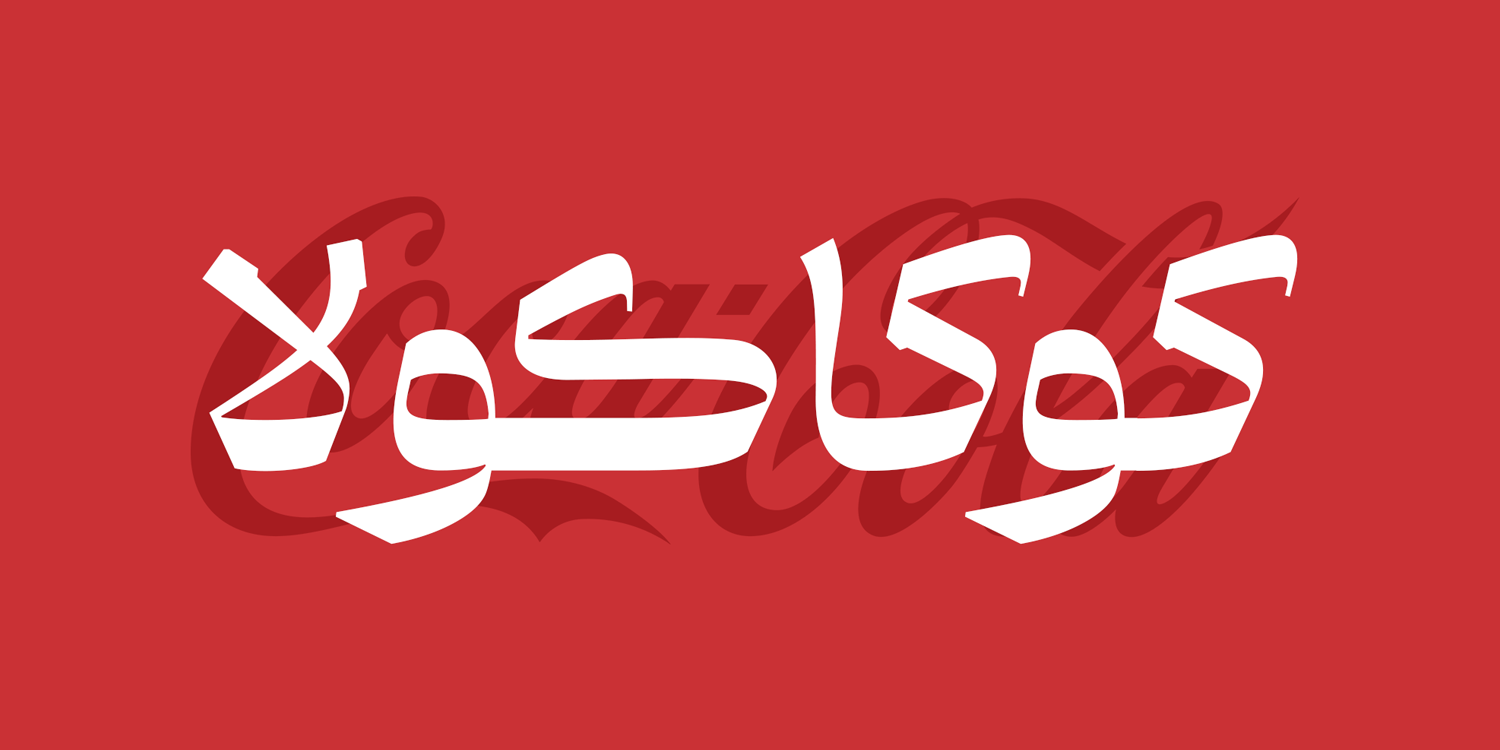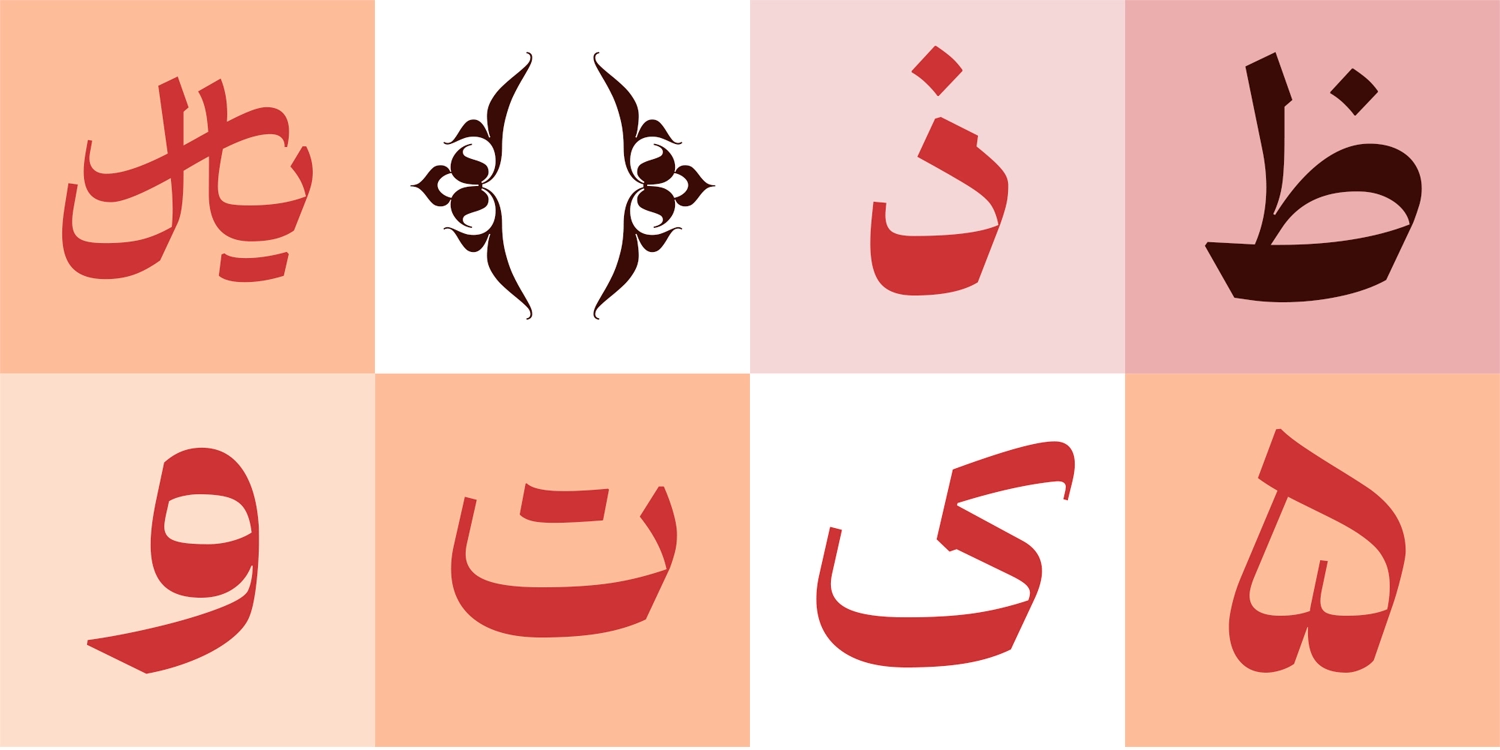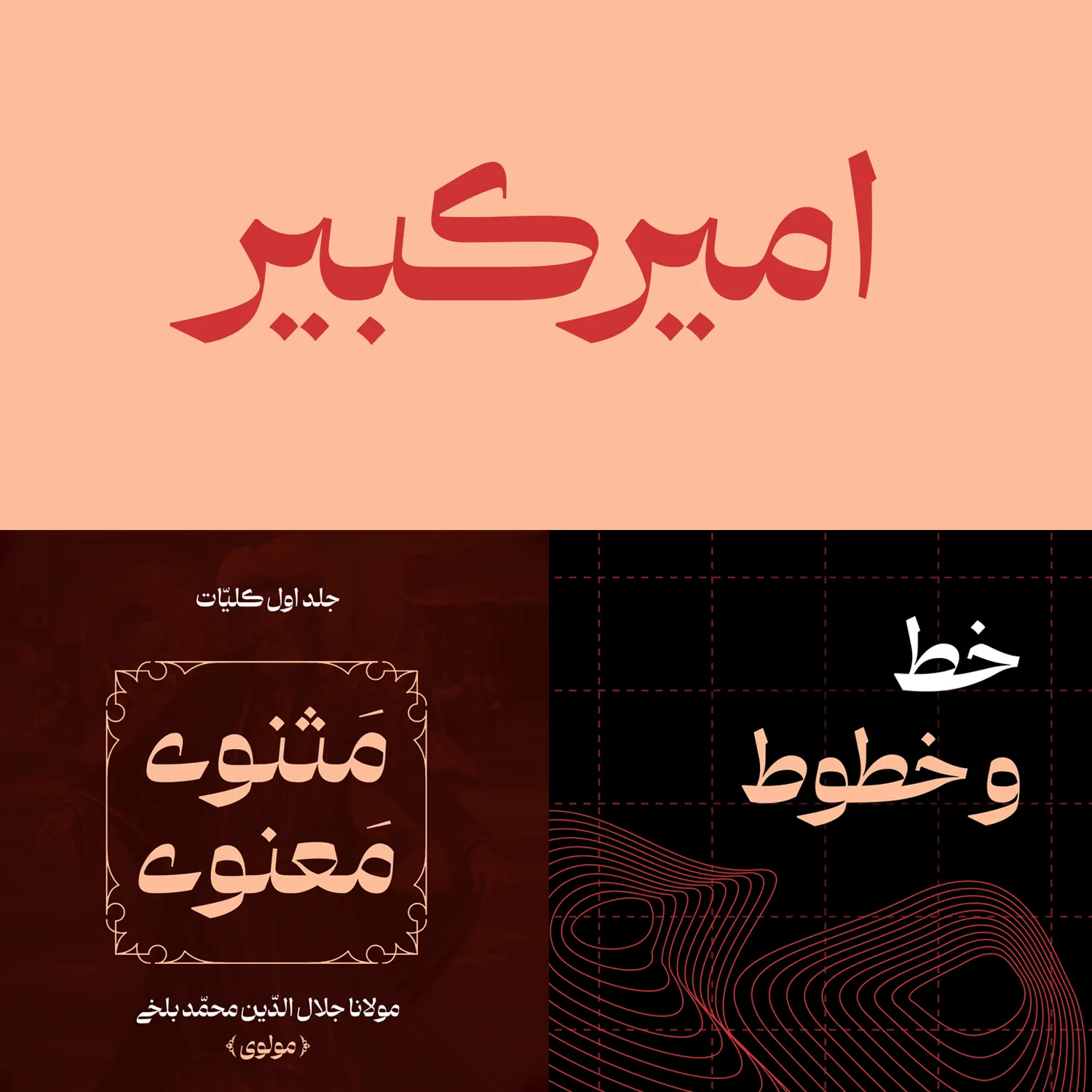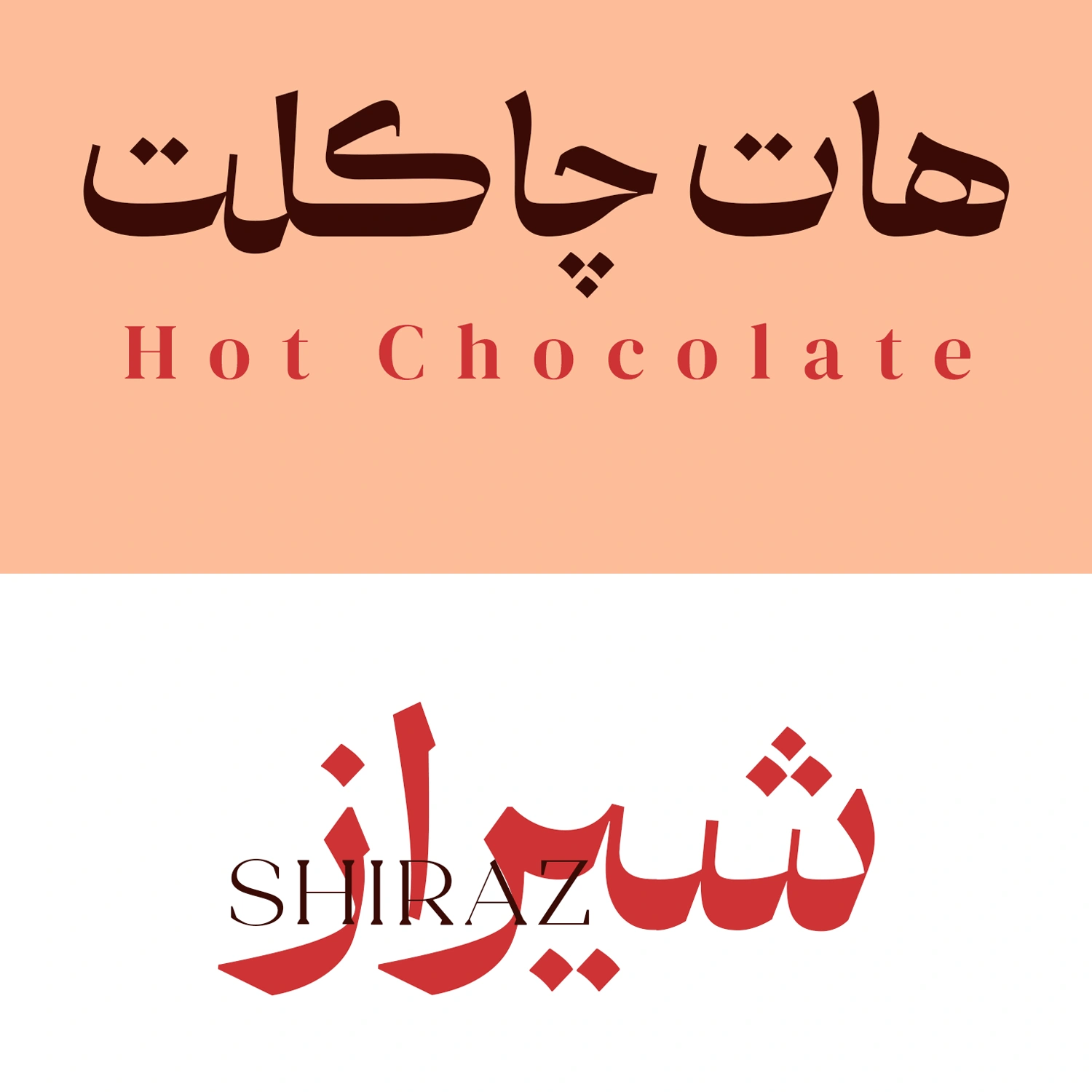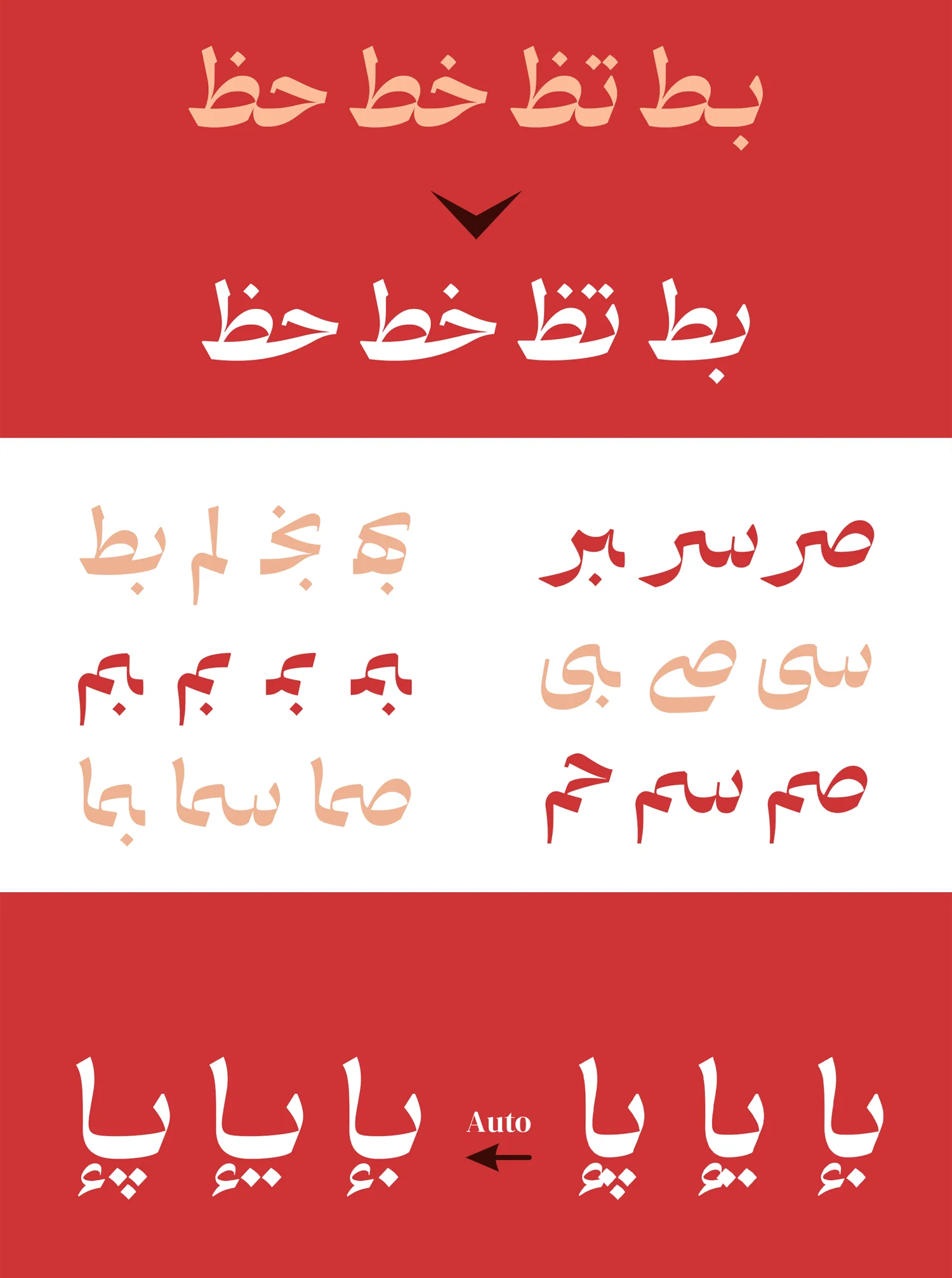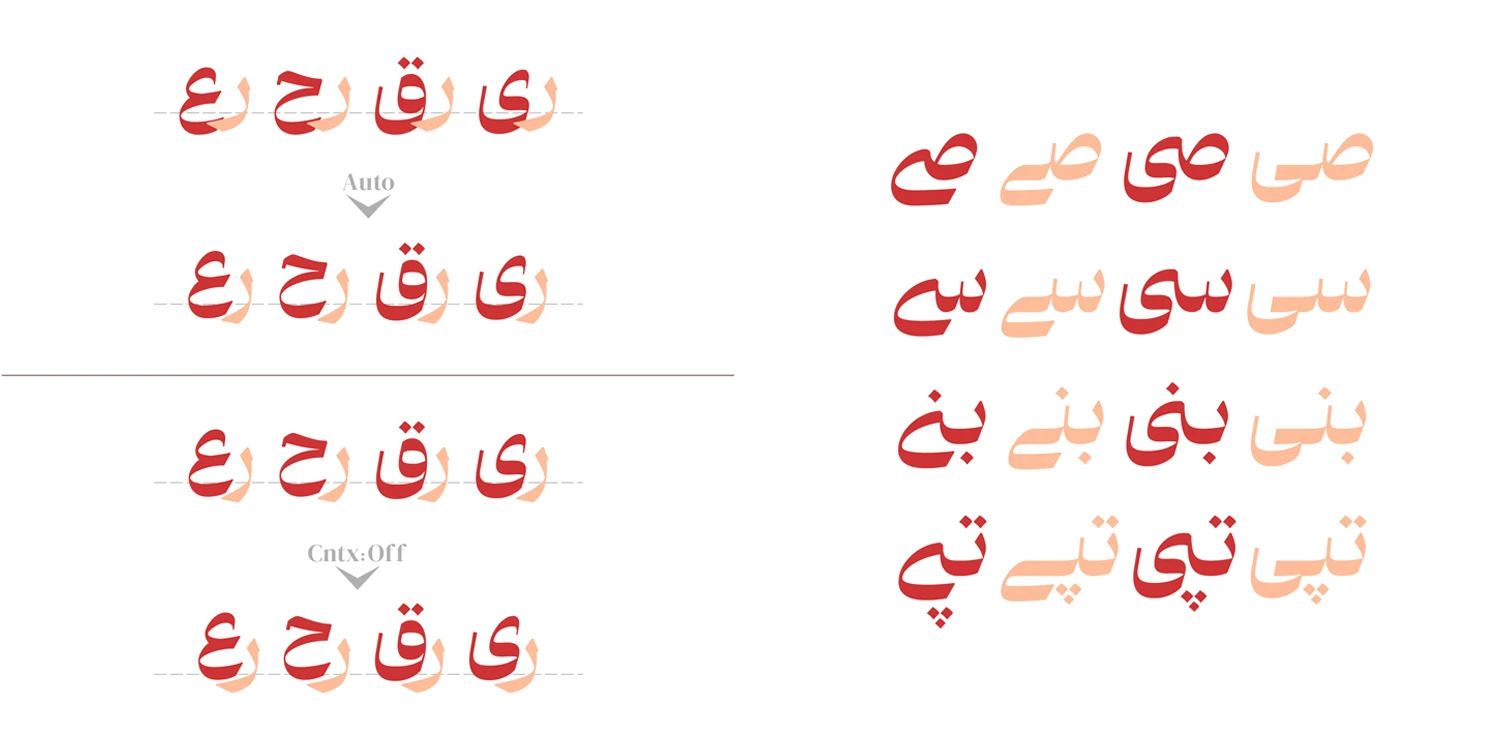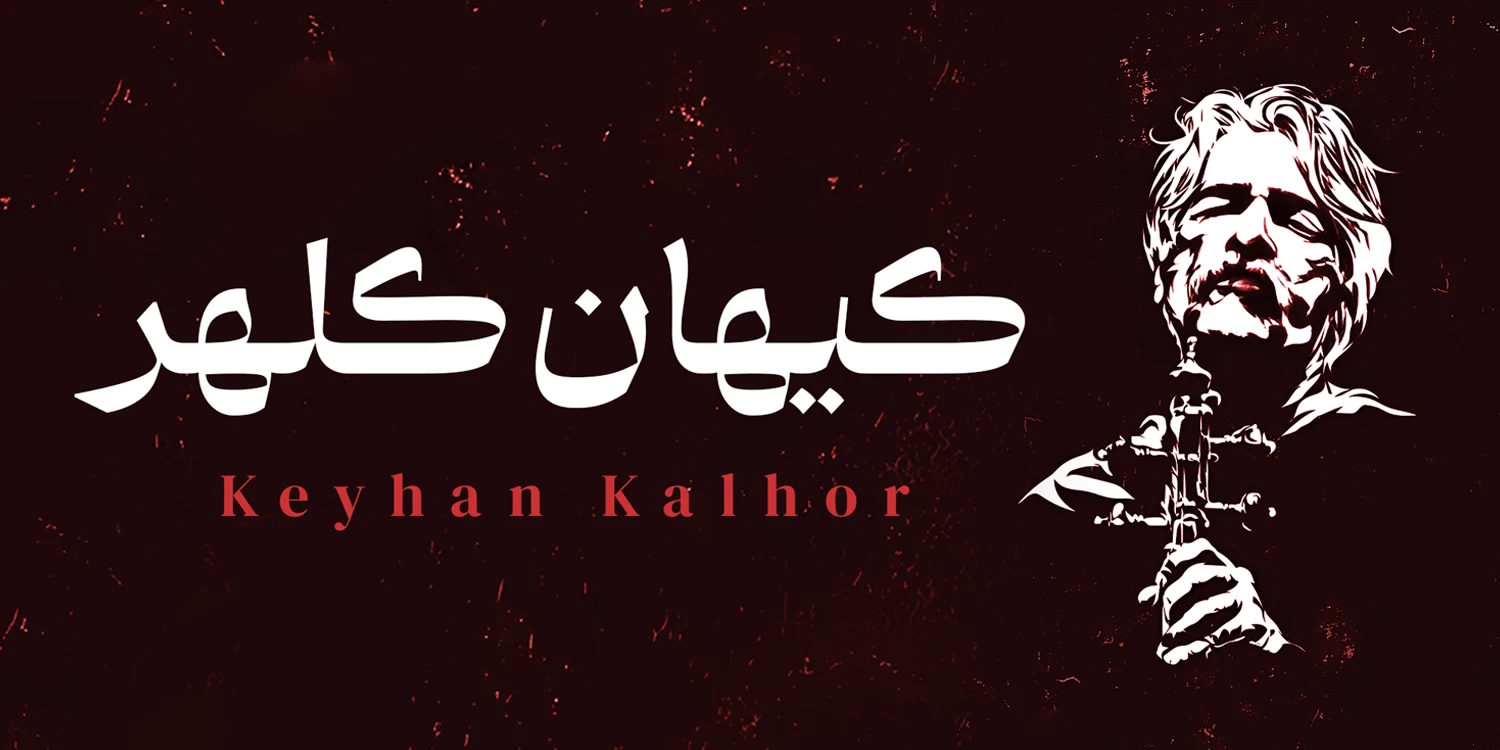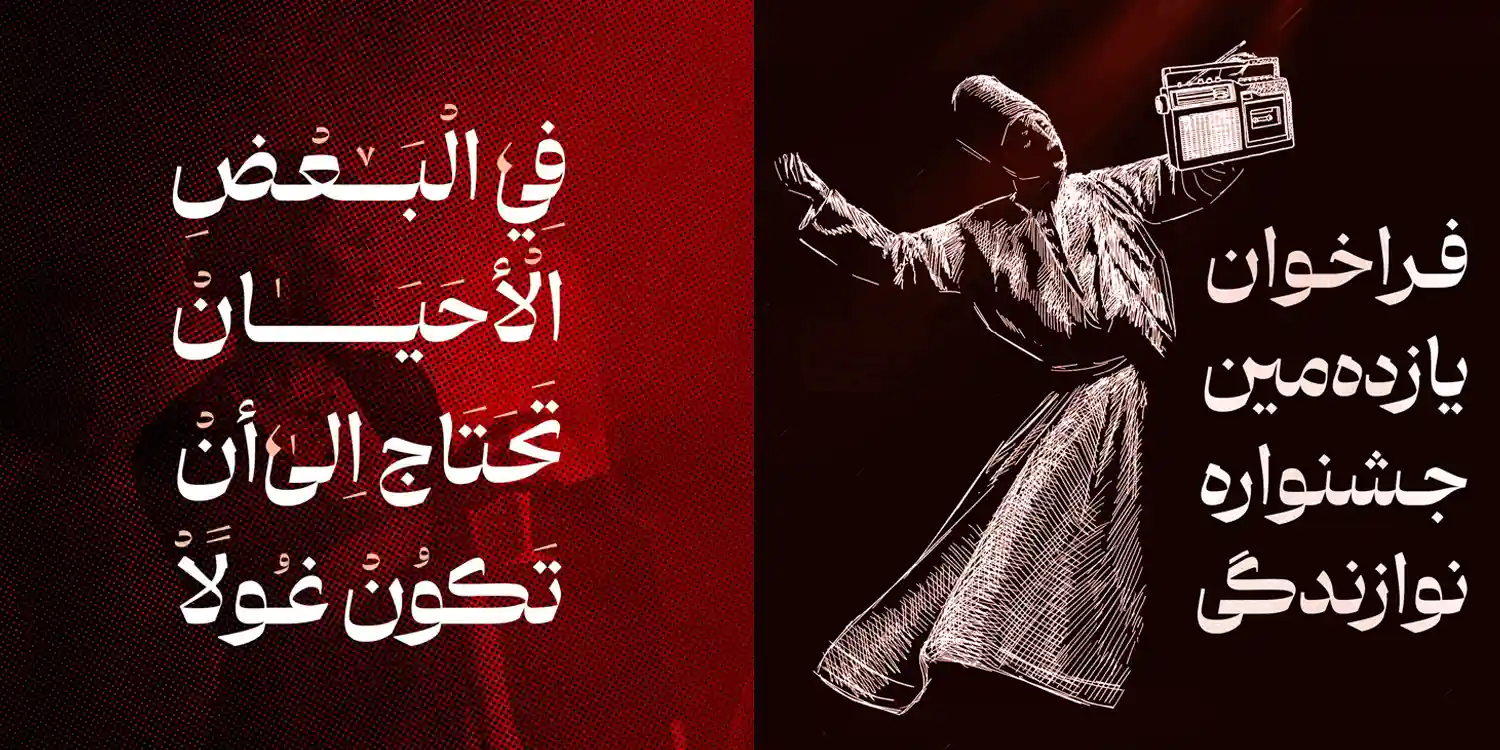
فونت دیوان (Divan)
فونت دیوان (به انگلیسی: Divan) از سری فونتهای جدید فارسی است که با الهام از خط ثلث، اما با ساختار نسخ تلاش کرده تا پلی میان قلمهای سنتی-ایرانی باشد. این فونت نمایشی از یک وزن سیاه Black پشتیبانی میکند که برای استفاده در عناوین، تبلیغات و پوسترها مناسب است. فونت دیوان رایگان نیست و در دسته فونتهای حرفهای قرار دارد.
حسین حیدری این قلم را به عنوان یک اثر هنری خلق کرده است که میتواند کاربردهای بسیار متنوعی داشته باشد. رایجترین آنها استفاده در طراحی پوسترهای تبلیغاتی است که بیشتر در موضوعات فرهنگی و هنری کاربرد دارد. در ادامه بیشتر با ویژگیهای این قلم آشنا خواهیم شد.
نقد و بررسی فونت دیوان (Divan)
این فونت یک نسخه مخصوص بدون حروف انگلیسی نیز دارد، که امکان ترکیب فونتهای لاتین دلخواه را برای کاربردهای چند زبانه فراهم میکند. فونت دیوان دارای ترکیبات (ligatures)، جایگزین اجباری و اختیاری است، که این ویژگیها در نرمافزارهای طراحی مانند Adobe Illustrator یا InDesign امکان تایپ کلمات را در چند حالت مختلف و نمایشی فراهم میکنند.
این ترکیبات، الهامگرفته از اصول خط ثلث، به ویژه در اتصالات حروف، انعطافپذیری بالایی ایجاد میکنند و از مشکلات رایج در فونتهای نمایشی فارسی مانند شکستگی متون جلوگیری میکنند.
تنوع بالای این فونت از زبانهای مختلف خاورمیانهای شامل گلیفهای تزئینی، واحدهای پولی مانند «ریال» برای ایران و اعراب است که به صورت استاندارد در کنار سایر حروف قرار میگیرند.
دیوان با اینکه فارسی است؛ اما محدود به این زبان نیست. عربی، انگلیسی، اردو، کردی، تورکی و جاوی از دیگر زبانهای پشتیبانی شده این قلم هستند. با پیوندی که زبان فارسی با فرهنگهای مختلف دارد، دیوان کمک میکند تا طراحی حرفهای را مطابق با این فرهنگها خلق کنید.
حروف جایگزین و نمایشی
فونت فارسی دیوان از حروف و ترکیبات جایگزین پشتیبانی میکند که برخی از آنها اختیاری، و برخی دیگر اجباری هستند. با استفاده از این ترکیبات میتوانید کلمات را با ساختارهای متفاوت تایپ کنید تا بر اساس موضوعی که دارند، تاثیر بهتری روی مخاطب بگذارند.
ترکیبات اجباری فونت نیز به منظور نمایشیتر کردن فونت و همچنین رفع ایرادات نمایشی که در صورت استفاده از گلیفهای استاندارد عادی استفاده خواهد شد در نظر گرفته شده است. این ترکیبات علاوهبر اینکه اتصالات حروف بهبود میدهند، ظاهری نمایشیتر دارند که به زیباتر شدن فونت کمک میکنند.
ترکیبات جایگزین این فونت برای تبلیغات یا عناوین که از ابعاد بزرگ برای تایپ کلمات استفاده شده باشد، ظاهری زیبا به نوشته شما خواهند بخشید. خصوصا وقتی از کاراکترهای تزئینی زبانهایی مثل اردو بر روی آنها استفاده شده باشد که ترکیب بین سنت و مدرنیته را برای موضوعات فرهنگی پیاده کرده باشید.
کاربردهای فونت دیوان
فونت دیوان Black برای متون طولانی توصیه نمیشود. اما در عوض برای عناوین، شعارهای تبلیغاتی و پوسترها که نیاز به فونتی نمایشی دارید، عالی است. از جمله این کاربردها میتوان به موارد زیر اشاره کرد:
- پروژههای فرهنگی و گرافیکی شامل طراحی پوستر و تصویر شبکههای اجتماعی.
- استفاده در تبلیغات درون شهری و صنایع چاپ روی بنر و بیلبوردهایی که در محیط شهر نصب میشوند.
- مناسب برای تامنیل و پوستر پست شبکههای اجتماعی عموما با موضوعات تاریخی و فرهنگی که به افزایش نرخ تبدیل کمک میکند.
- استفاده در عنوان جلد کتاب و مجلات بیشتر با موضوعات تاریخی و فرهنگی.
فونت دیوان قلمی با سبک سنتی ایرانی است که سعی کرده ارتباط خطوط ثلث و نسخ را با دنیای مدرن امروز مستحکمتر کند. از این فونت میتوانید در موضوعات مختلف دیگری استفاده کنید.